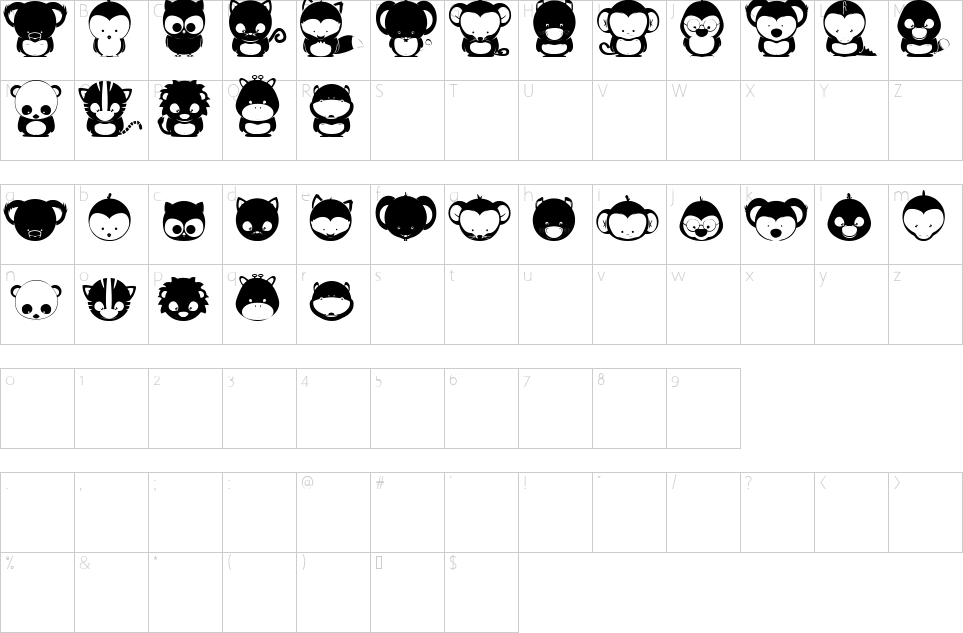
Descubra Animox, uma fonte elegante e versátil projetada pela talentosa designer Maelle Keita. Animox é perfeita para qualquer projeto que valorize estilo e modernidade. Esta fonte foi criada para atender a demanda por uma fonte de qualidade que seja adequada tanto para uso em projetos gráficos profissionais quanto para uso pessoal. Animox é uma fonte fácil de usar e sua simplicidade torna-a perfeita para criações em alta velocidade. Animox já foi baixada 12,882 vezes, mostrando que esta fonte não está apenas de bom gosto, mas também está se destacando como uma opção popular para designers e gráficos. Download Animox agora e transforme seu trabalho em uma obra-prima única e contemporânea.